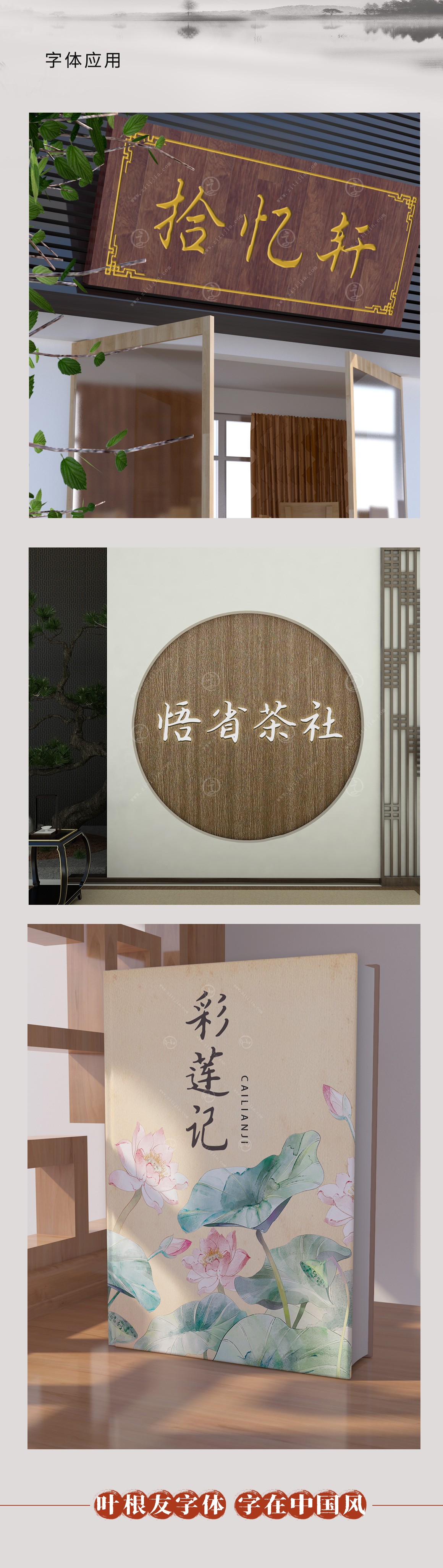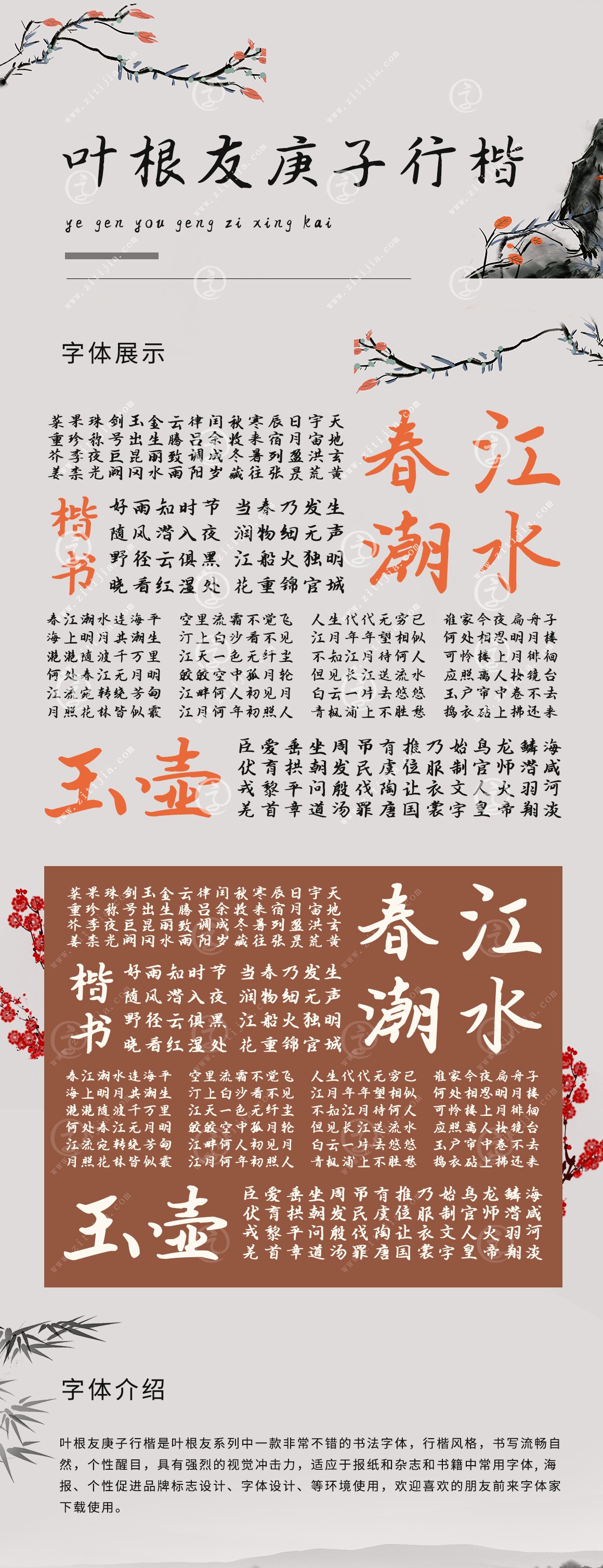
葉根友庚子行楷是一款非常不錯(cuò)的手寫字體,書(shū)寫流暢自然,具有強(qiáng)烈的視覺(jué)沖擊力,適應(yīng)于報(bào)紙和雜志和書(shū)籍中常用字體, 海報(bào)、個(gè)性促進(jìn)品牌標(biāo)志設(shè)計(jì)、字體設(shè)計(jì)、等場(chǎng)景使用。